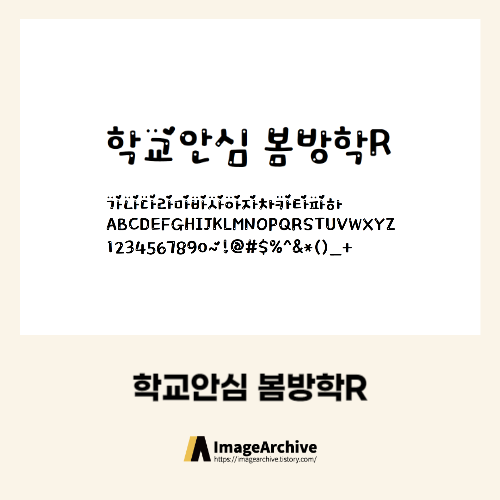
학교안심 봄방학체
아기자기한 느낌의 귀여운폰트
학교안심 봄방학은 두꺼운 매직펜으로 쓴 듯한 획의 두께감에 하트와 동그라미, 반짝임 등의 장식을 더하여 한 글자만써도 주목도 있는 폰트입니다. 글자수를 적게 사용하는 이름표, 시간표, 스티커, 영상 자막의 짧은 표현이나 의성어, 의태어 등에 활용도가 높을 것으로 예상됩니다.
손글씨 느낌의 폰트에 하트와 동그라미모양을 넣어서 귀엽고 산뜻한 느낌을 더한 폰트로 아이들이 좋아할만한 요소를 많이 갖추고 있어 사용빈도도 높을것으로 생각되네요. 학교안심폰트라 저작권걱정없이 자유롭게 사용할 수 있어요.
학교안심 봄방학R